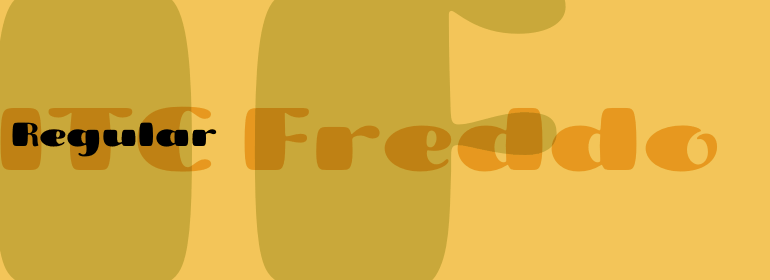
ITC Freddo™
ITC Freddo是纽约设计师James Montalbano的作品,其灵感来自20世纪30年代的一本标牌刻字手册。 Montalbano喜欢这本手册中刻画的字符形状,但发现许多比例很奇怪。因此,他根据现在的标准对它们进行了重新的诠释,创作了大写字母和小写字母,使他们之间可以更好地相互补充。
ITC Freddo is the work of New York designer James Montalbano and was inspired by a sign lettering manual from the 1930s. Montalbano liked the character shapes illustrated in this manual but found many of the proportions odd. So he reinterpreted them to produce capitals and lower case letters which, according to today's standards, better complement one another.